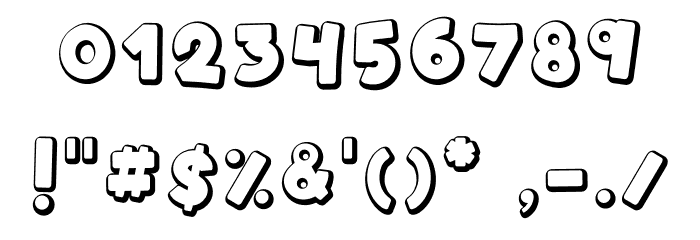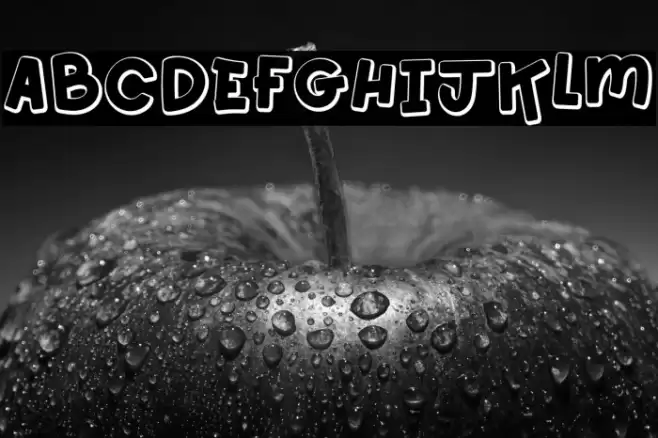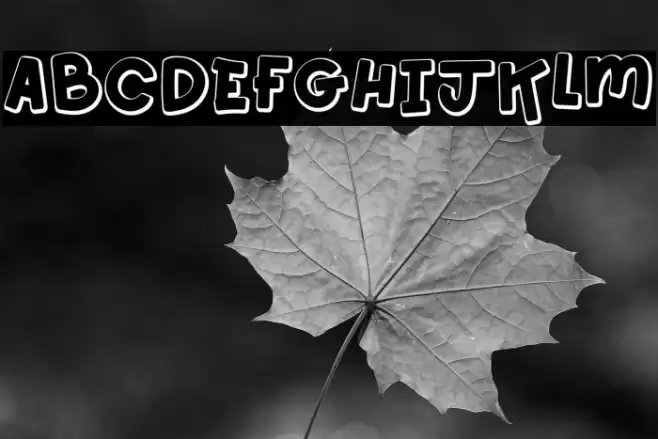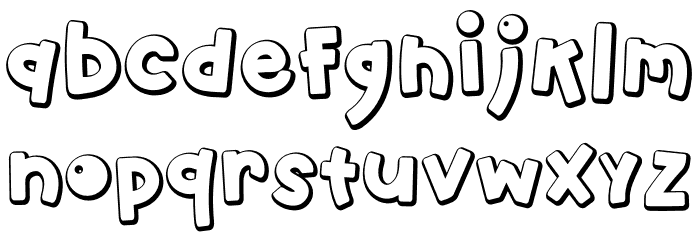
Frozen Gnome Font
| Style général | Playful, Whimsical |
| Projets proposés | Ideal for children's books, comic strips, playful branding, party invitations, and educational materials. |